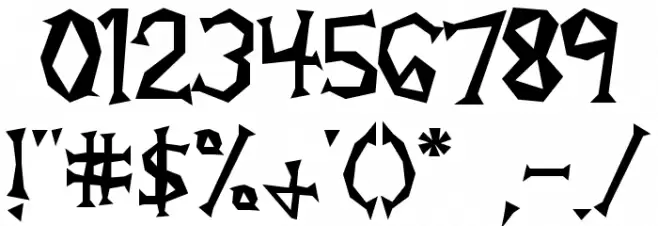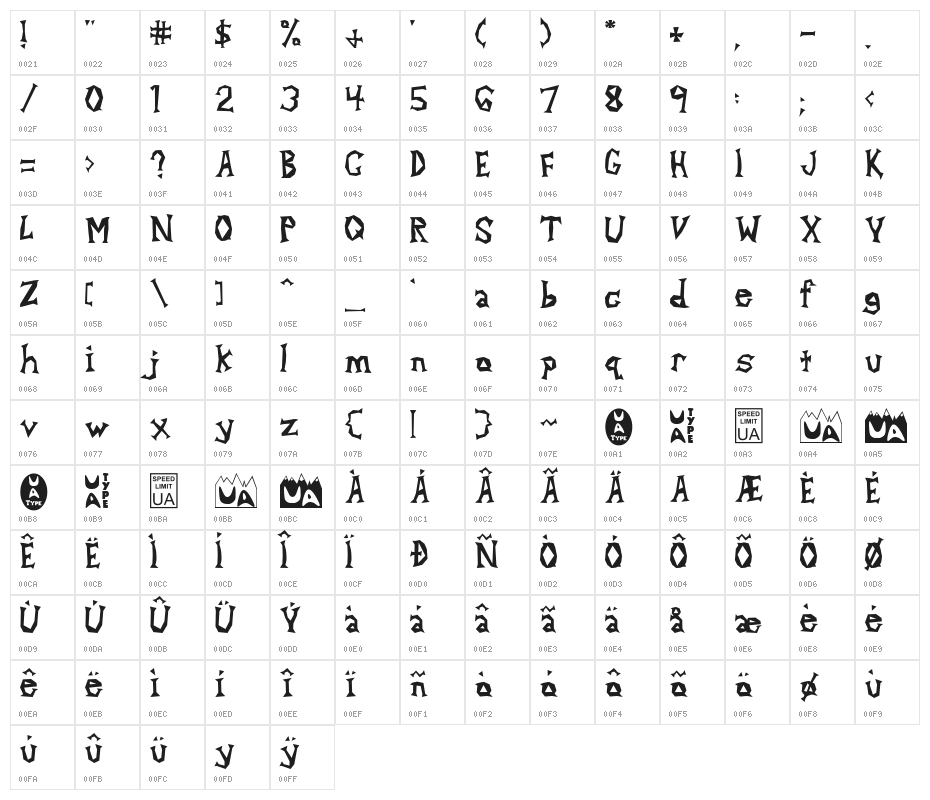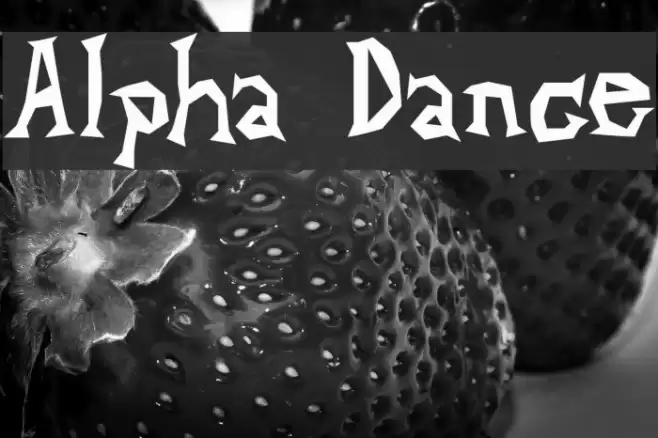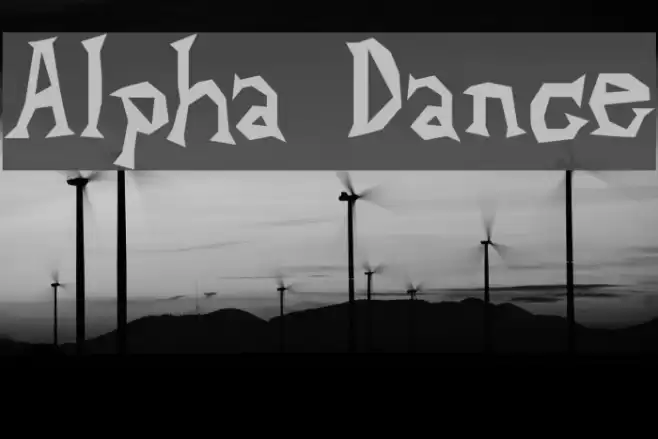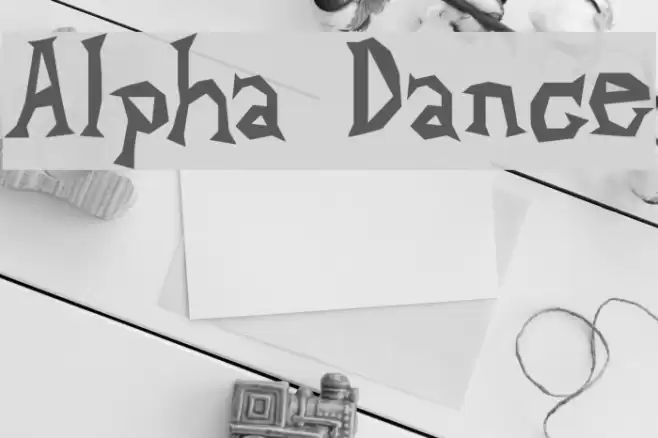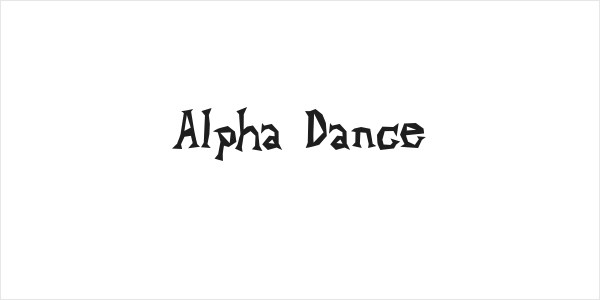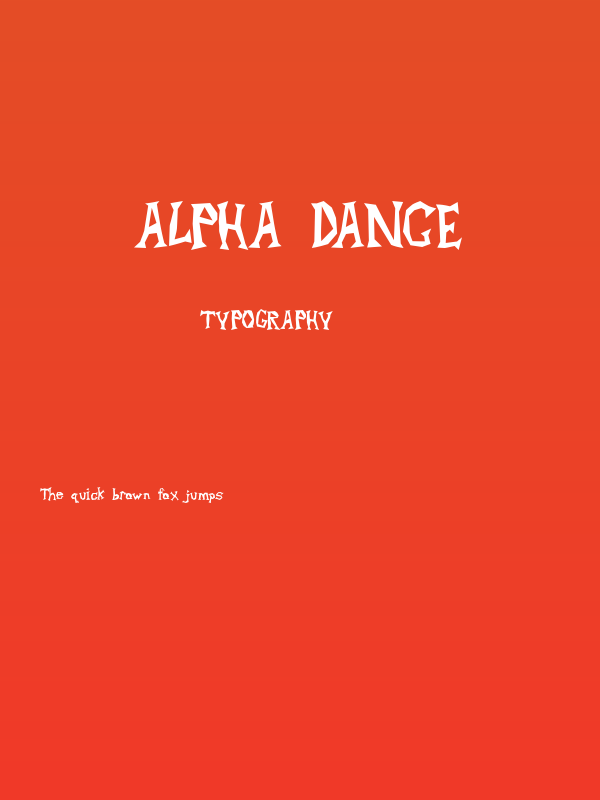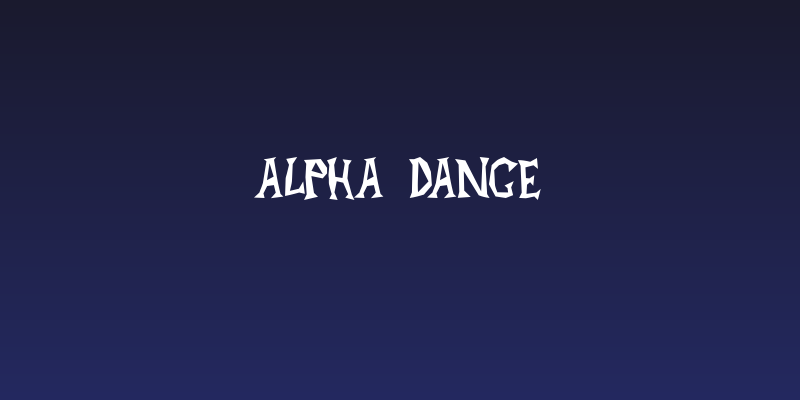
Alpha Dance Font
| 全体的なスタイル | Modern, Decorative |
| おすすめプロジェクト | Perfect for music album covers, event posters, video game titles, and branding that requires a bold statement. |